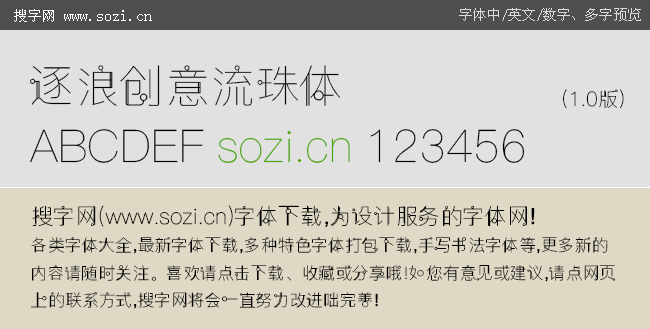
逐浪創(chuàng)意流珠體
搜字網(wǎng)提供一款逐浪創(chuàng)意流珠體中文藝術(shù)字體下載,逐浪創(chuàng)意流珠體是一款用于線條設(shè)計(jì)方面的字體,該字體線條非常纖細(xì),字形符合當(dāng)代人的審美規(guī)則,整體效果非常出眾,適合應(yīng)用于廣告設(shè)計(jì)、名片設(shè)計(jì)、包裝印刷、產(chǎn)品設(shè)計(jì)等應(yīng)用。